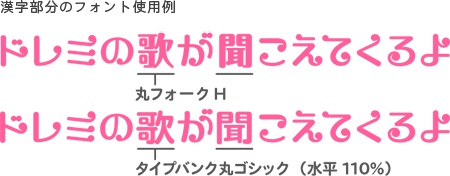
ななキュンのうたフォント
とことん可愛いフォントを!と思って製作しました。丸ゴシックのような優しい印象で、音符のようなカールした部分が超可愛いフォントです。親しみやすくキュートな雰囲気を醸し出すのでPOPなデザインにもマッチします。 動作環境 Mac:システム/OS X対応(10.x)〜最新のOS X Windows:OS/日本語版Windows2000、XP、VISTA、Windows7、Windows8、Windows10 フォント形式:OpenTypeフォント 収録文字数について ひらがな、カタカナのみの書体になります。 安心して使えるロイヤリティフリーの書体 あらゆる商用・デザイン用途(印刷物・ゲーム・アプリ・映像・動画・ロゴ・同人作品)に使用できる、商用申請の必要のないロイヤリティフリーの書体になります。文字の加工・変形も可能です。ご安心ください。 イラストレーション:つゆこ様 個性的なデザインに注目した日本語フォントのダウンロード販売。物語の奥行きを感じさせるセンスの良いフォントは、あなたのデザインに深みとおもしろみを与えます。安心して使える商用利用可のオリジナルフォントです。